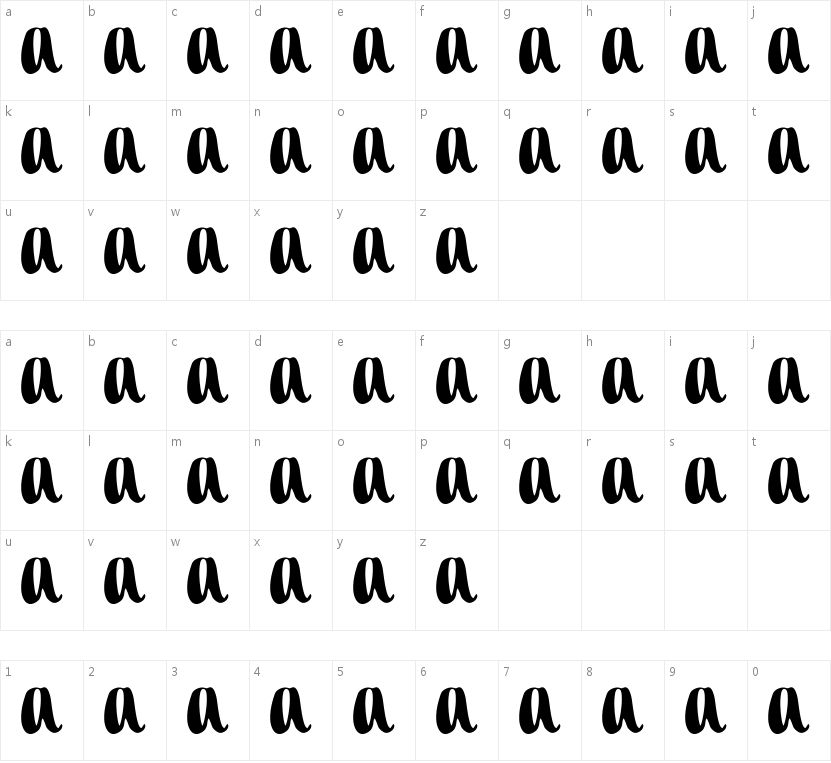
happyycoda
Happyycoda字体是一种具有充满活力和欢快感的手写风格字体。这种字体有着流畅的笔画和鲜艳的颜色,非常适合用于各种卡片、海报、广告等场合,以增添它们的生气和活力。同时,Happyycoda字体也可以用于设计个性化的各种文本,包括书籍封面、T恤设计、商标设计等。这种字体的风格非常独特,让人看了很容易感到愉悦和快乐,带来了一种轻松的感觉。 Happyycoda字体非常容易阅读,并且在各种尺寸和屏幕上都能够清晰地显示,是一种非常实用的字体。无论是在印刷品还是数字媒体上,Happyycoda字体都能够让设计作品更具魅力和吸引力。
happyycoda是一款非常不错的手写艺术字体,具有很好的视觉感,适合于文化类的宣传设计、商业类品牌的广告和产品包装设计以及个性化文字排版等较多场景。
happyycoda字符映射图